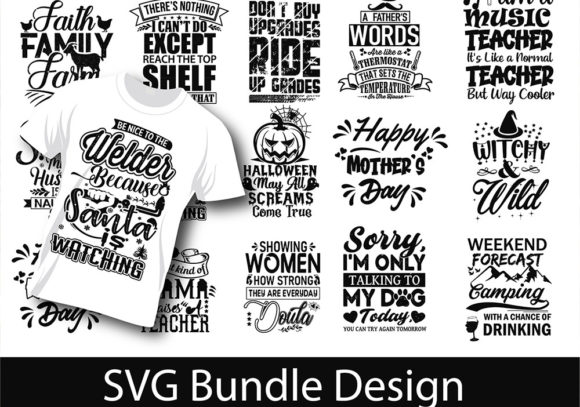
Free Typography Design
Free Typography Designのような高品質の素材をお探しの場合、このプレミアムパッケージはクリエイティブなプロジェクトに素晴らしい選択です。
POD(オンデマンド印刷)製品、結婚式の招待状、またはソーシャルメディアのグラフィックを作成している場合でも、Free Typography Designは理想的です。